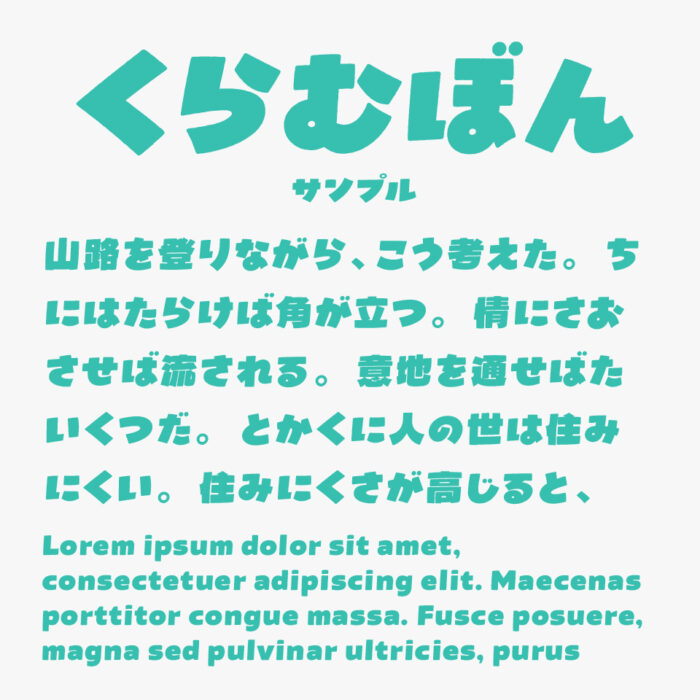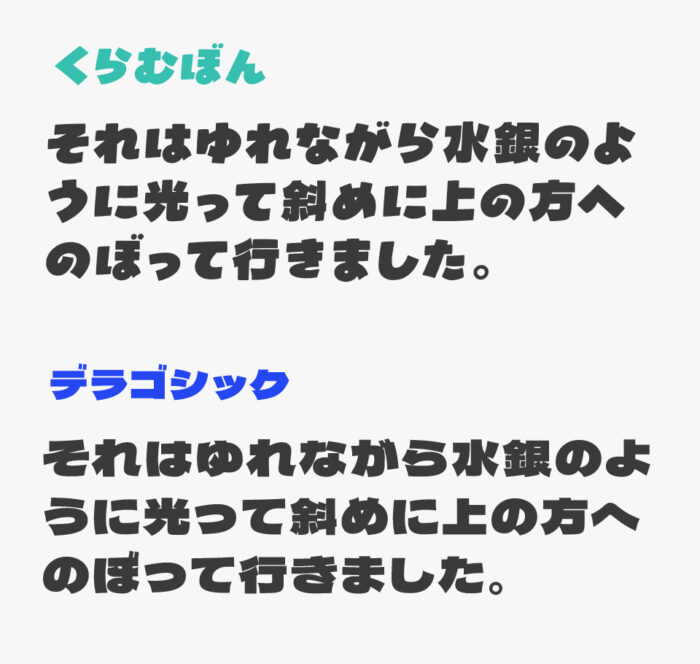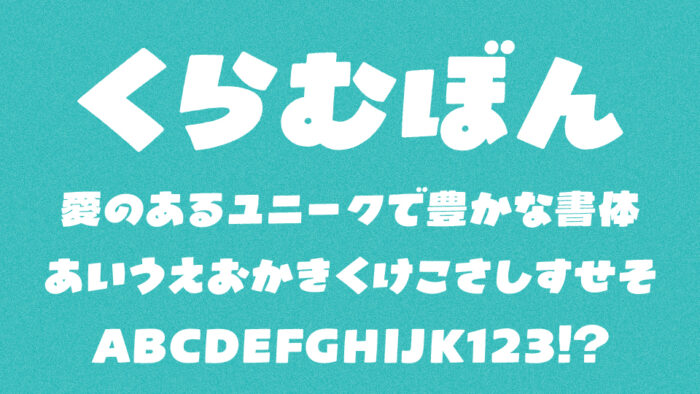
くらむぼんフォントは、デラゴシック(DelaGothic)を膨らませて、ギザギザな処理を施し、ひらがなとカタカナとアルファベットはオリジナルの文字に置き換えて作られているデザインフォントです。
デラゴシックの超極太なフォルムはそののままで、ボンッと弾むような動きがある可愛さをもち、柔らかなシルエットがとても素敵フォントとなっています。
比較してみると、デラゴシックのどっしり感な雰囲気はそのままで、オリジナルに作られているひらがなとカタカナによって、柔らかく親しみやす雰囲気になっています。
| 漢字 | ○(JIS第一〜第三水準漢字まで収録)) |